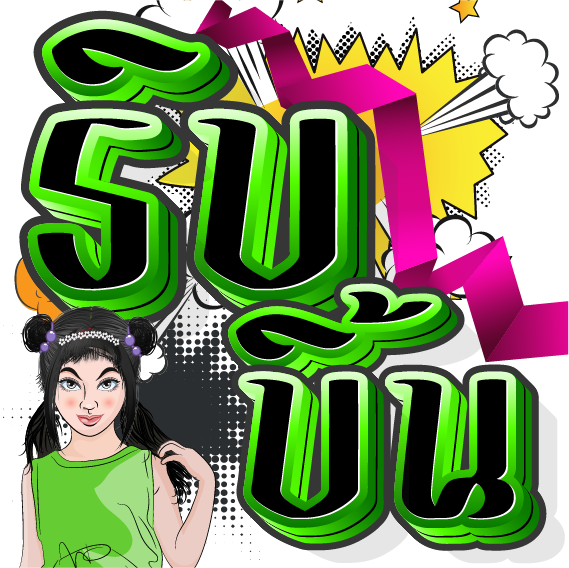
ฟอนต์ริบบิ้น
ฟอนต์ริบบิ้นบรัช อักษรป้ายลายมือ จากอดีตจากที่เคยเขียนด้วยพู่กัน ป้ายผ้า งานศิลป์ โฆษณา อาทิต่างๆมากมาย
หลากหลายลายมือผู้เขียน จนกลายเป็นอัตลักษณ์เฉพาะ ที่โดดเด่นเป็นสง่ามีความเป็นศิลปะงดงามลงตัว ของผู้เขียนนั้นๆ